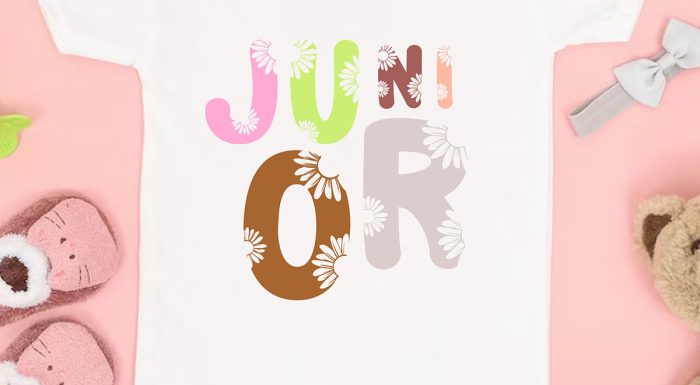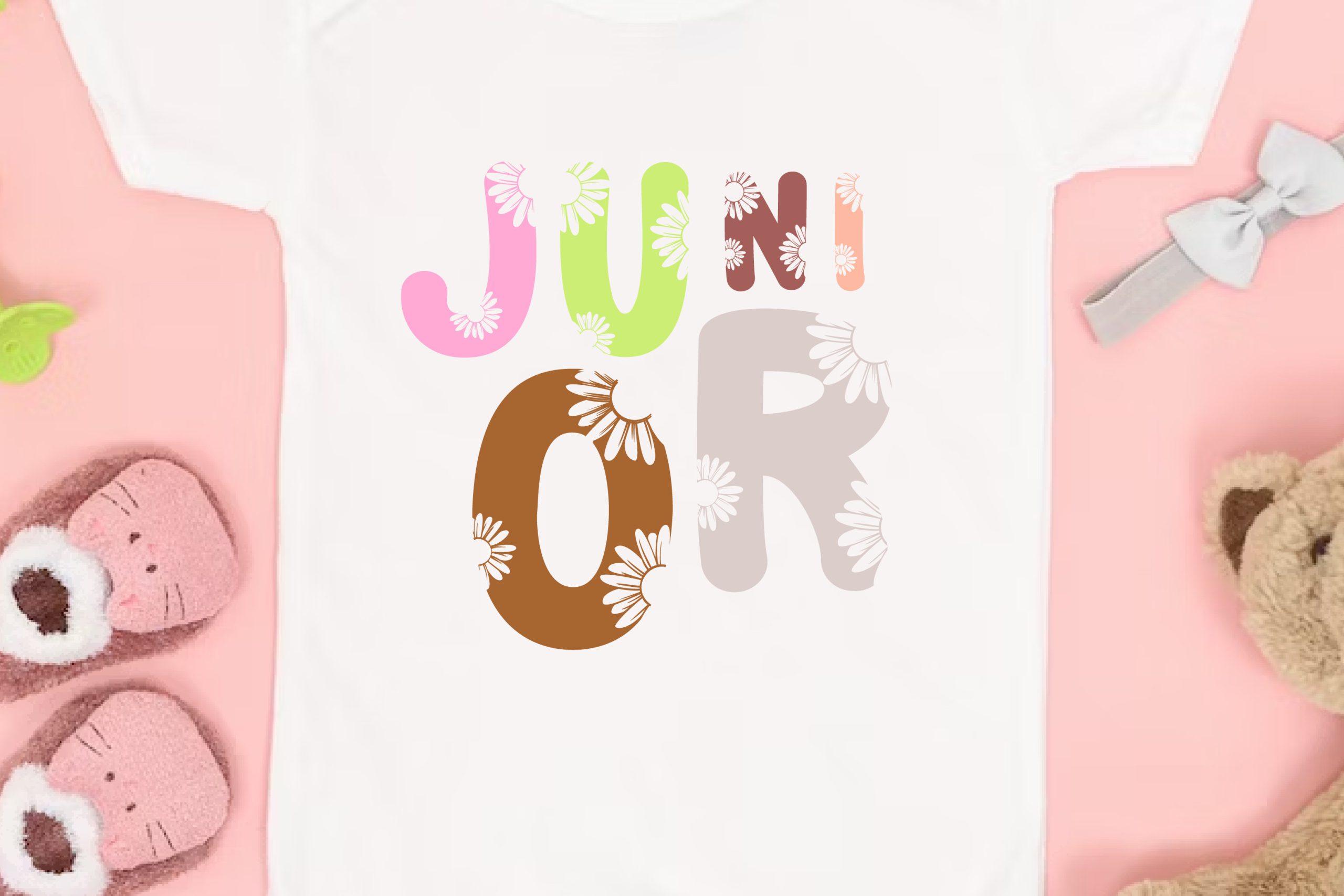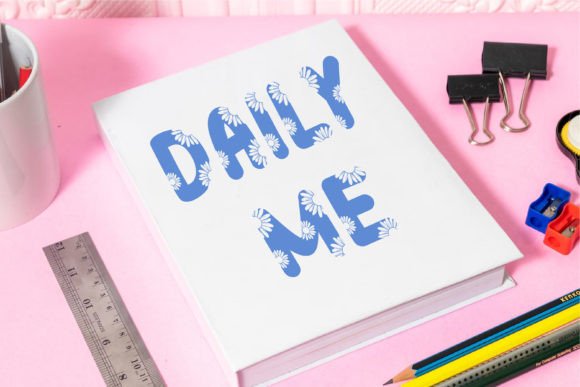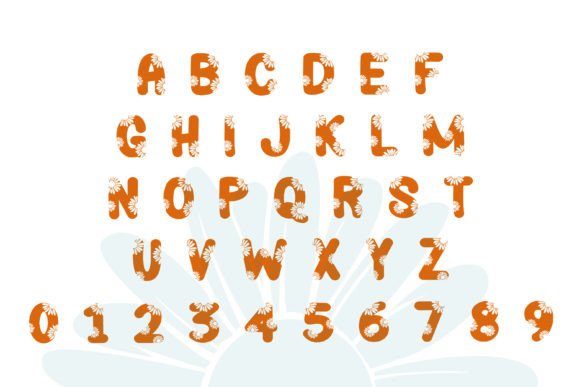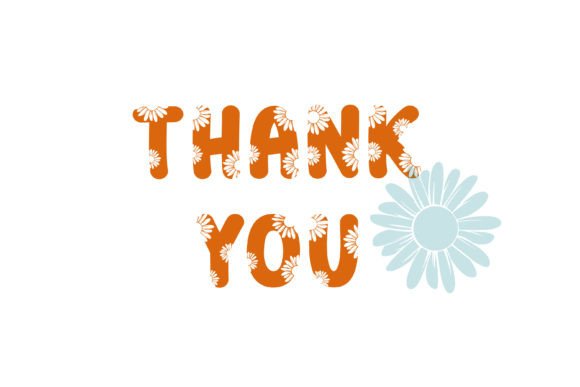
فونت Hi Daisy انگلیسی
دانلود فونت Hi Daisy انگلیسی Font های دیزی |
| ⭐ مجموعه فونت | دانلود فونت انگلیسی سلام دیزی Font Hi Daisy |
| ⭐ توضیحات | معرفی Hi Daisy Font، حروفی عجیب و تزئینی که حال و هوای شاد و بازیگوشی را به طرح های شما می بخشد. این فونت با حروف عجیب و غریب و شکوفایی جذاب خود، جوهره شادی و دوستی را به تصویر می کشد. قلم Hi Daisy که برای کارتهای تبریک، کتابهای کودکان و پروژههای خلاقانه ایدهآل است، حسی از هوس را اضافه میکند و باعث میشود متن شما با شادی و خلاقیت شکوفا شود. |